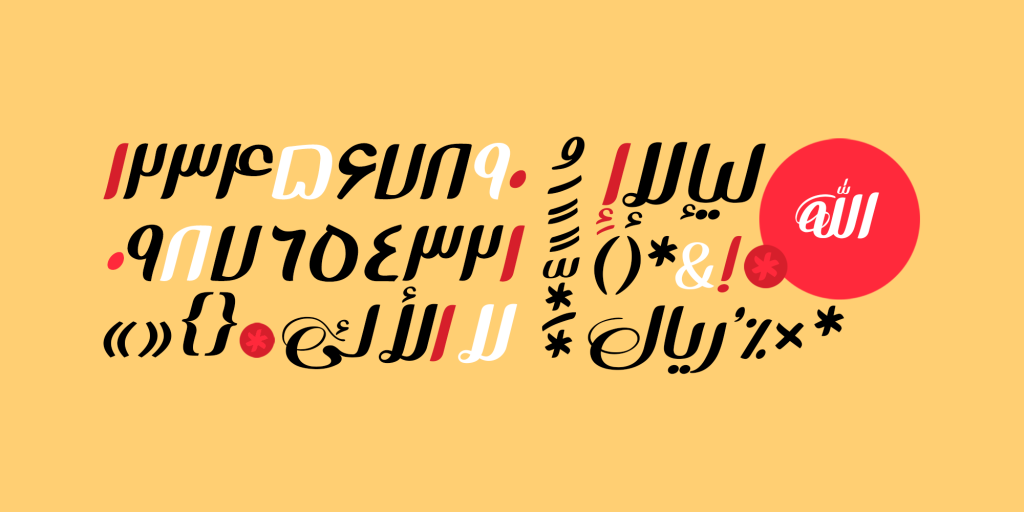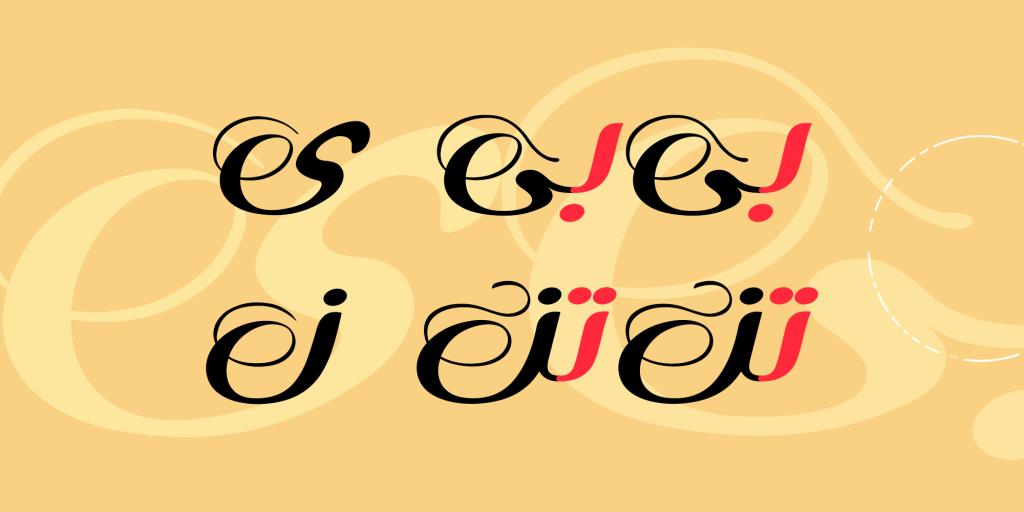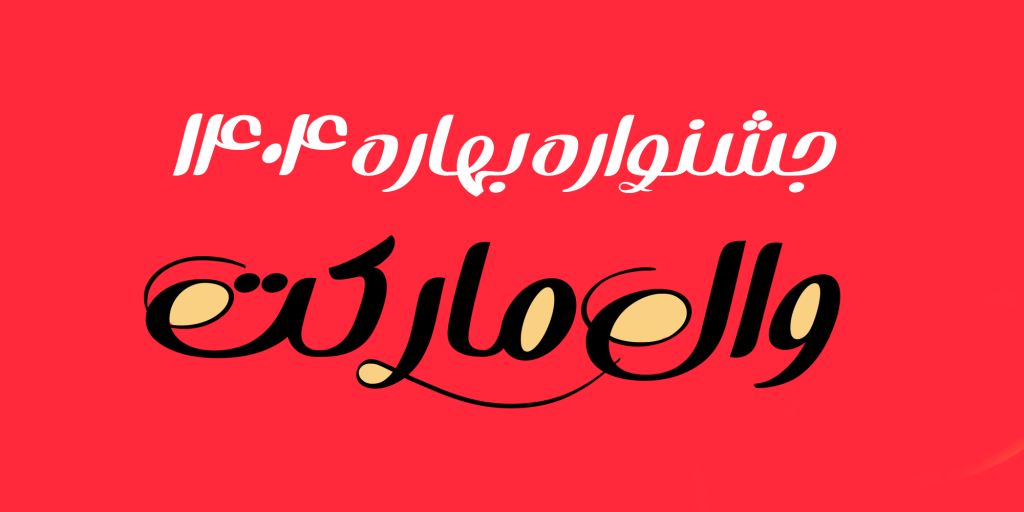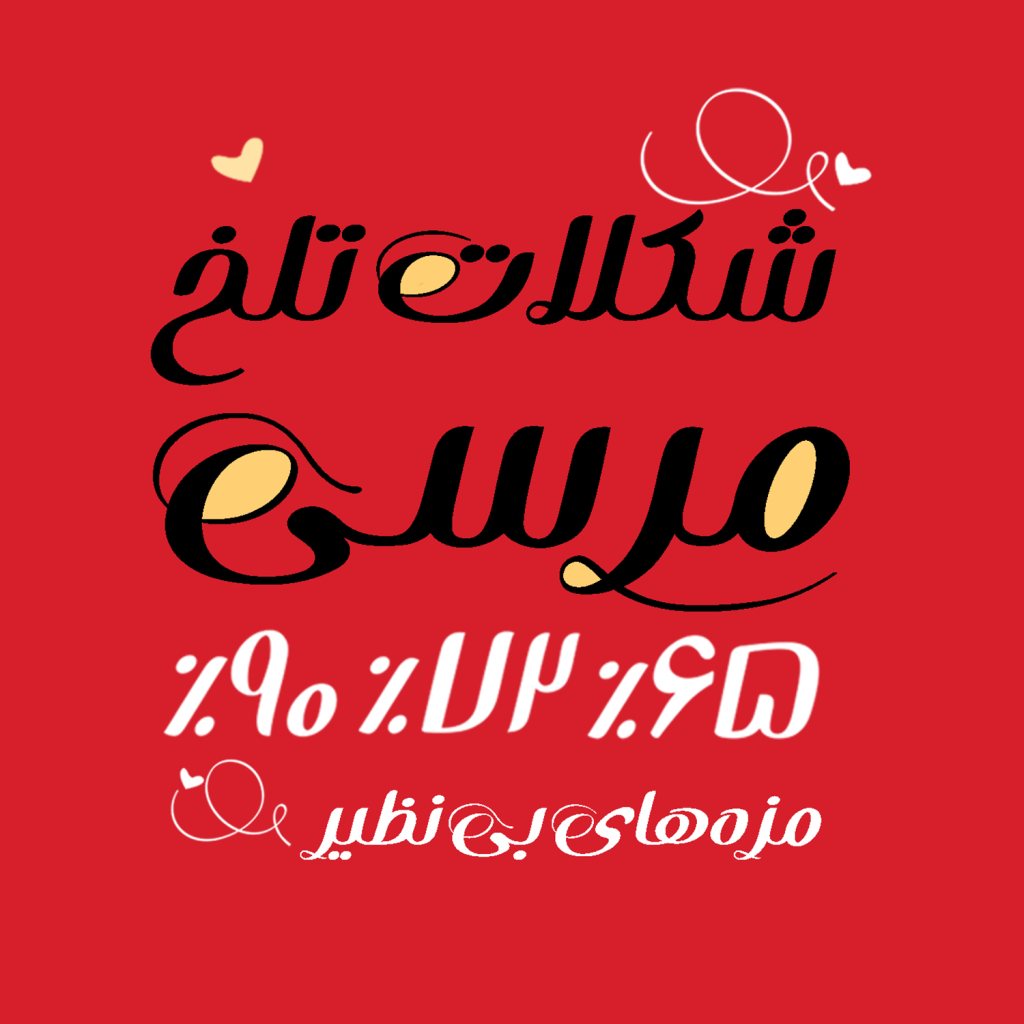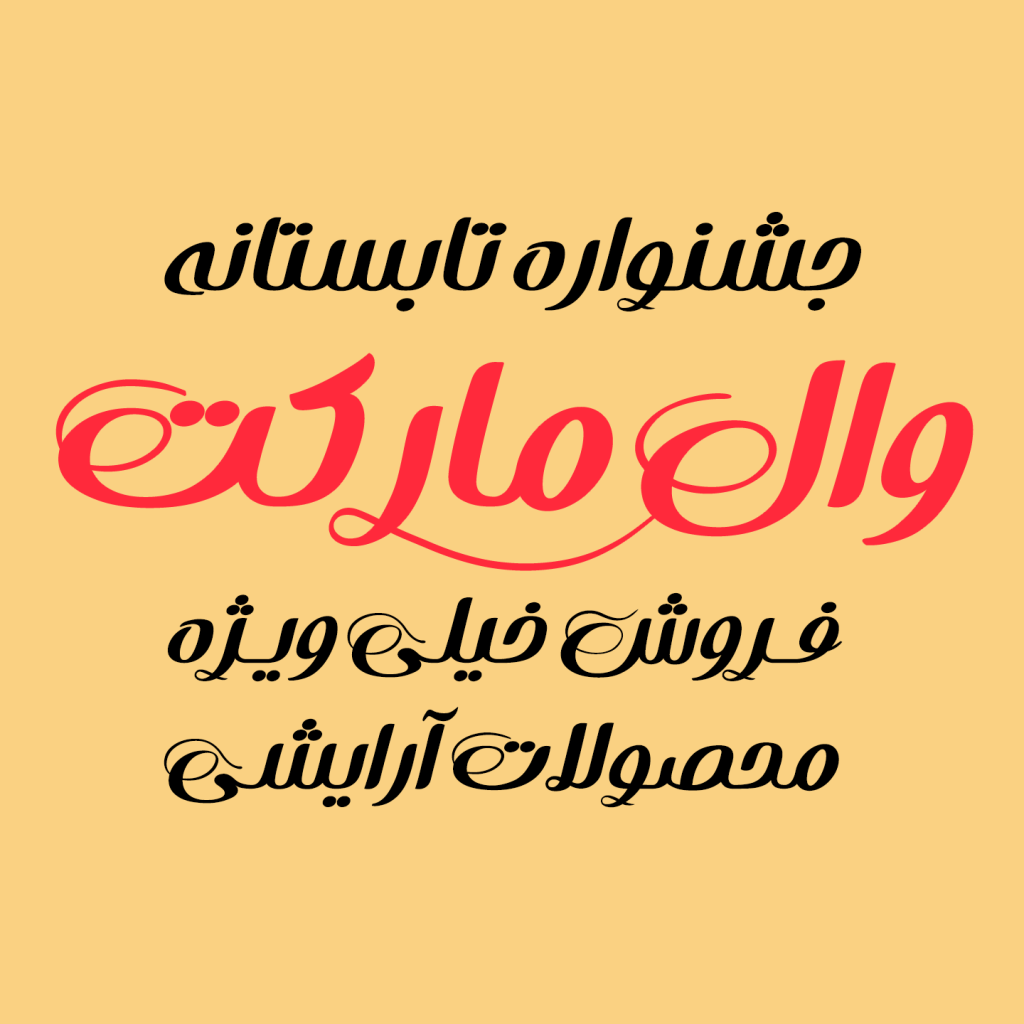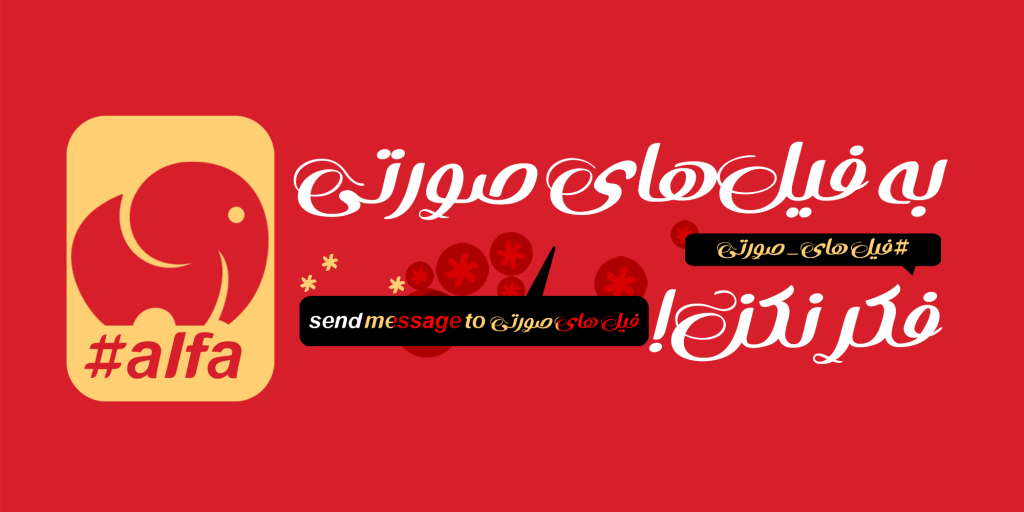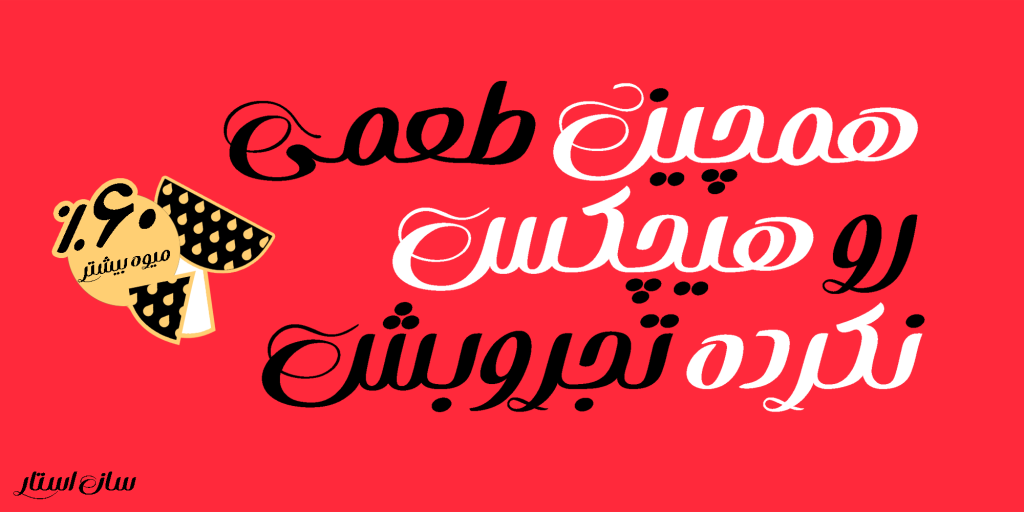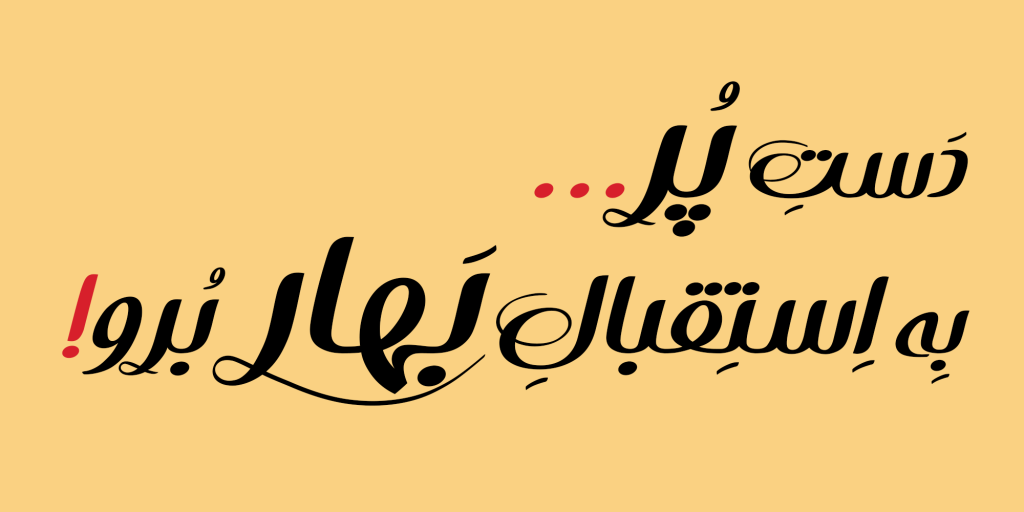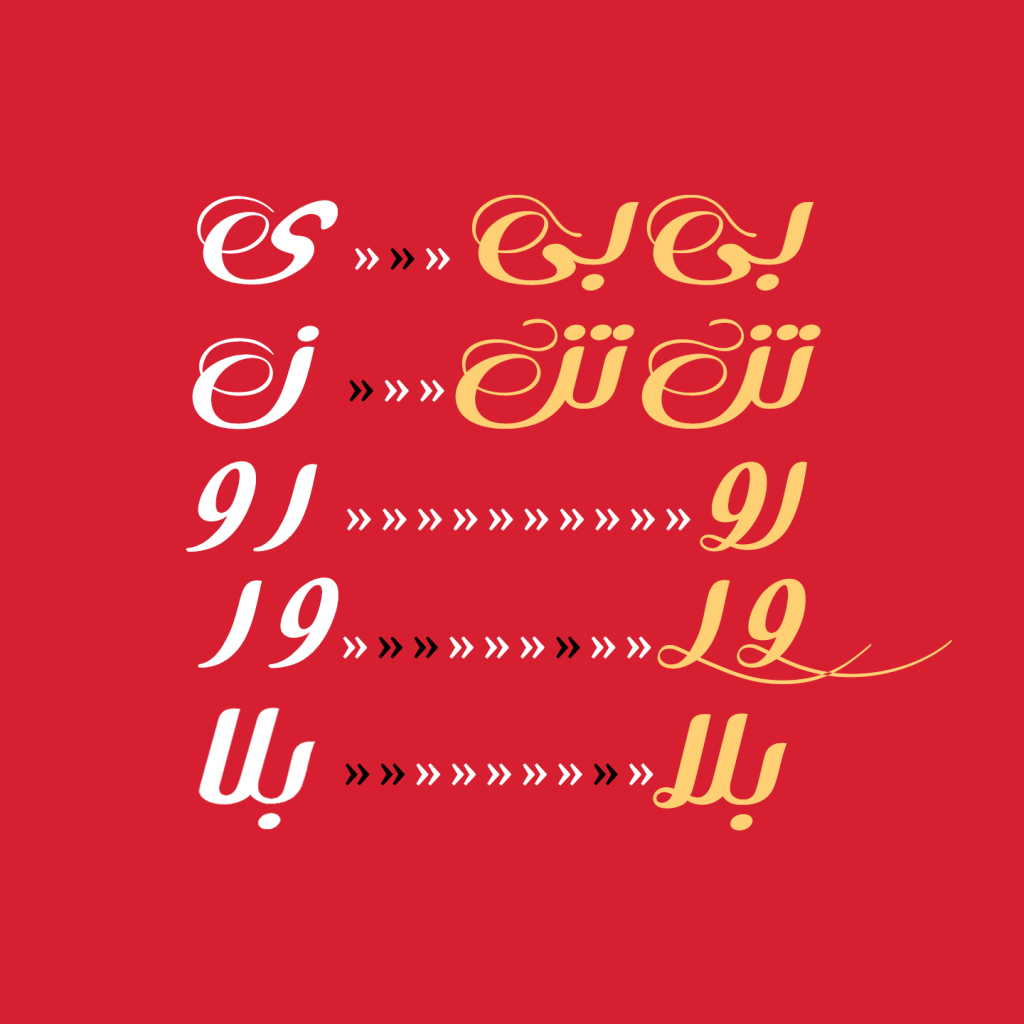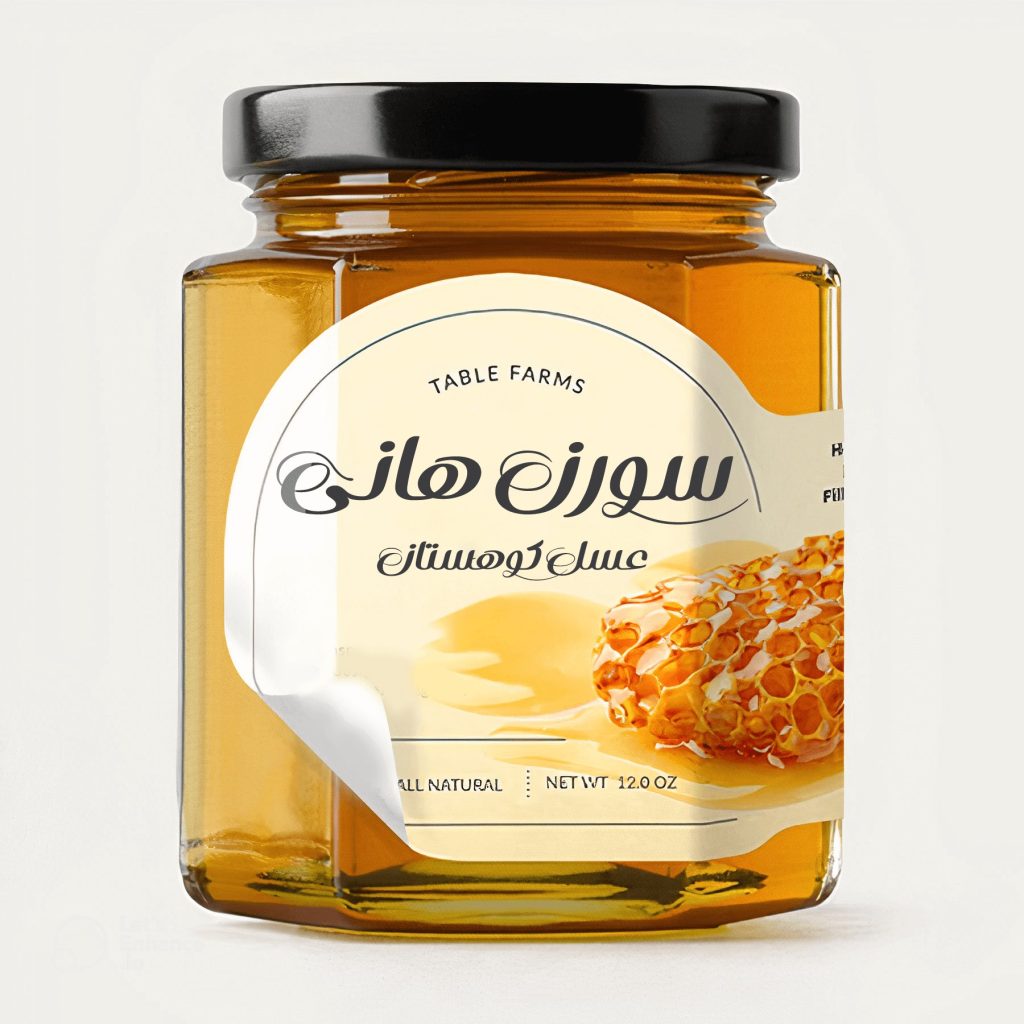
فونت بهار رقصان و مهربان
فونت بهارمهربان و دلنشین است و ظاهری امروزی و لوکس دارد. خطوط و شکل های خاص در طراحی حروف و گلیف های این تایپ فیس حس نزدیک بودن و صمیمیت را به خواننده القا می کند. و بیشتر برای برقراری ارتباط احساسی، عاطفی و مثبت در فضای گرافیکی کاربرد دارد.
ویژگی های اصلی این قلم قوس ها و پیچ های به شدت اغراق آمیز آن است که در انتهای حروف متصل و منفصل دیده می شود. دارای ویژگی نمایشی است تا نگاه خواننده را به خود جب کند. رهایی و جسارت در قلم بهار مثال زدنی است . بهار می رقصد بازیگوش است تا تجربه ای متفاوت را به تایپوگرافی فارسی بیفزاید. قوسهای این قلم با هدف کمک به فضاسازی اطراف حروف طراحی شده و به همبستگی ترکیببندیهای مختلف در قالب لوگوتایپ، جملات تیتر، شعارهای تبلیغاتی و ترکیبهای تایپوگرافی کمک میکند.
بهار از کنتراست ملایم در سطح بهره مند است به گونه ای که حروف در قسمت خط کرسی زمینه، نازک شده و هنگام فاصله گرفتن از خط زمینه به تدریج ضخیم میشوند. این روند برخلاف حرکات صعودی و نزولی در حالت نسخ است و به همین دلیل حالت لاتینایز به فونت داده و ساختار حروف را منطبق بر سبکهای مدرن میکند به شکلی که برخی حروف شبیه به حروف لاتین دیده میشوند.
پشتیبانی از زبان و ترکیبات مختلف
بهار فونتی چند زبانه است که به غیر از زبان فارسی از زبان های عربی و کوردی نیز پشتیبانی می کند. همچنین دارای ترکیبات جایگزین بسیاری در دل خود است از جمله حروف «ر» و «و» که در حالت های متصل و منفصل به دو شکل ساده و کرشمه دار استفاده می شود. فعالسازی این ویژگی ساده است و در راهنمای فونت توضیح داده شده است. در زیر تصاویری نمونه از این قلم زیبا را برای شما آورده ایم.